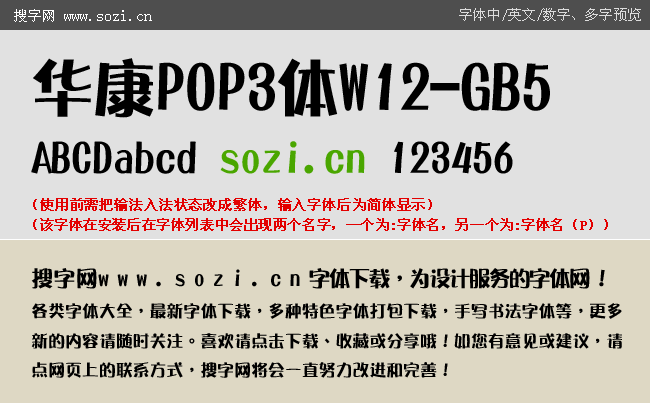
華康POP3體-GB5
搜字網(wǎng)提供華康POP3體-GB5字體下載,華康POP3字體采取橫細直粗的線條表現(xiàn)手法,有別于傳統(tǒng)POP字體的漢字容易結成一塊,不易突顯出手寫文字的個性,由于此字體造型方正飽滿,充分傳達出現(xiàn)代文字藝術的體現(xiàn)。適合海報設計、畫冊排版、廣告宣傳等設計應用。